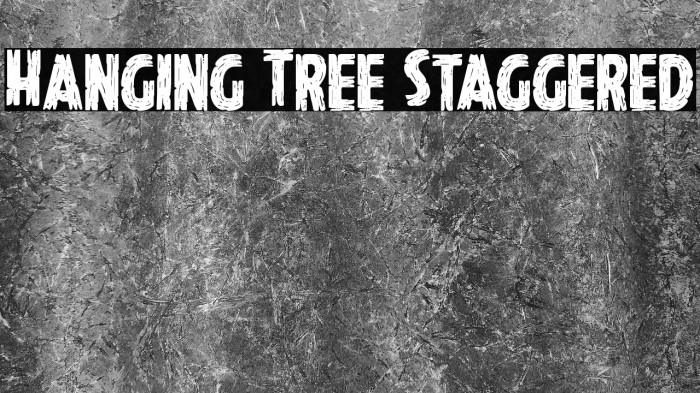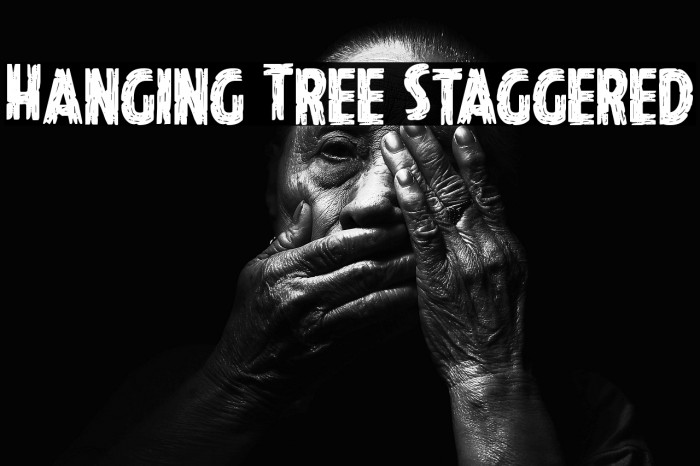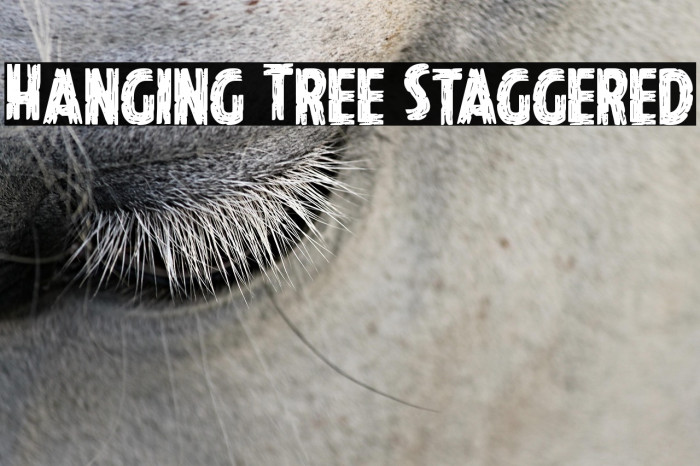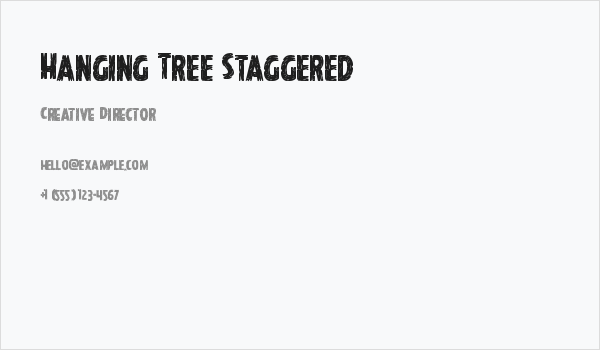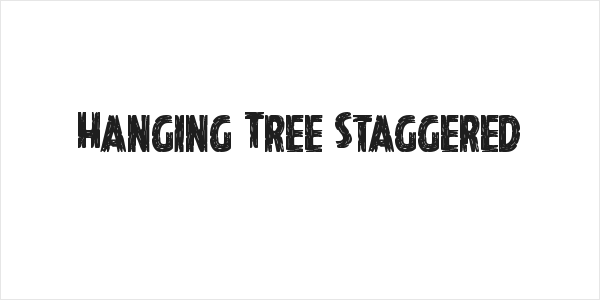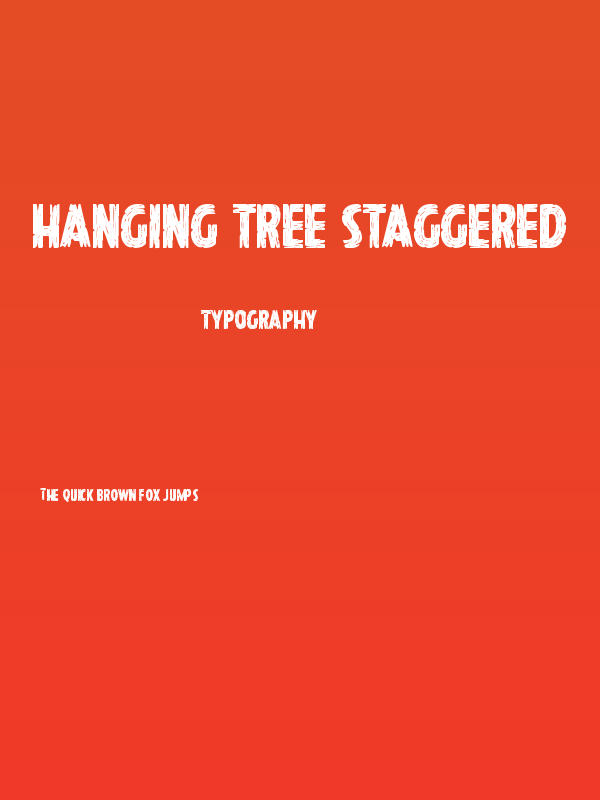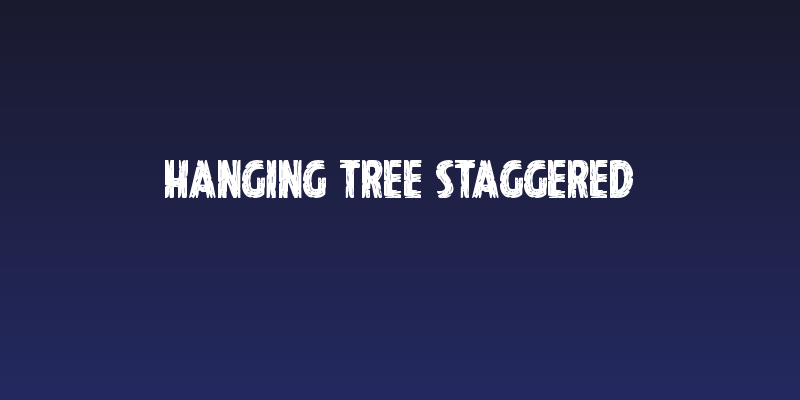
Hanging Tree Staggered Font
✎ Messy
| Vorgeschlagene Projekte | Ideal for posters, album covers, branding for outdoor or rustic-themed products, and any project needing a bold, artistic touch. |